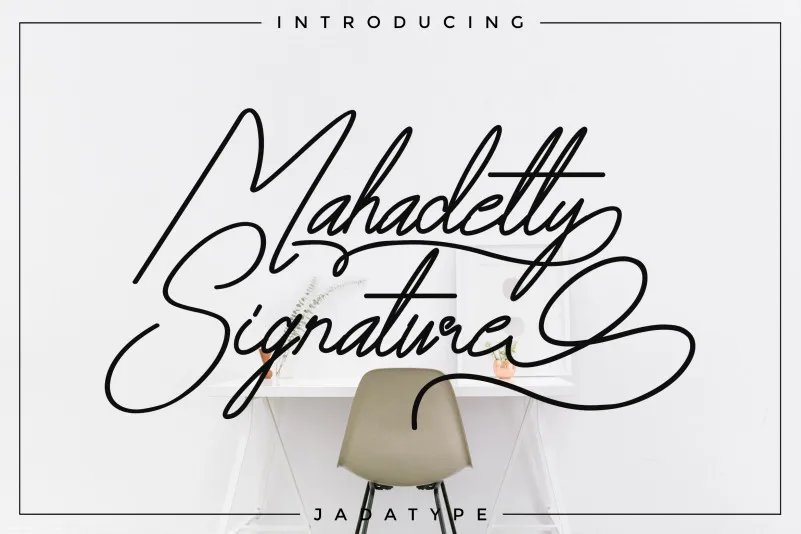
Mahadetty Signature Font – Download Grátis
Introduzimos a Mahadetty Font, uma elegante script font que é ideal para seus próximos projetos de design! Este font é perfeito tanto para marca quanto para projetos românticos. A Mahadetty foi criada por Jadatype e apresenta um desenho meticuloso, apesar da primeira impressão ser um pouco caótica. É uma fonte monolínea, perfeita para criar ambientes carregados de estilo e elegância, especialmente para nomes de marca ou projetos românticos como cartões personalizados. Inspirada em passar momentos especiais com alguém querido, a Mahadetty é um toque único e refinado que vai deixar seu design brilhar. Que tal experimentar o charme desta fonte neste projeto especial?